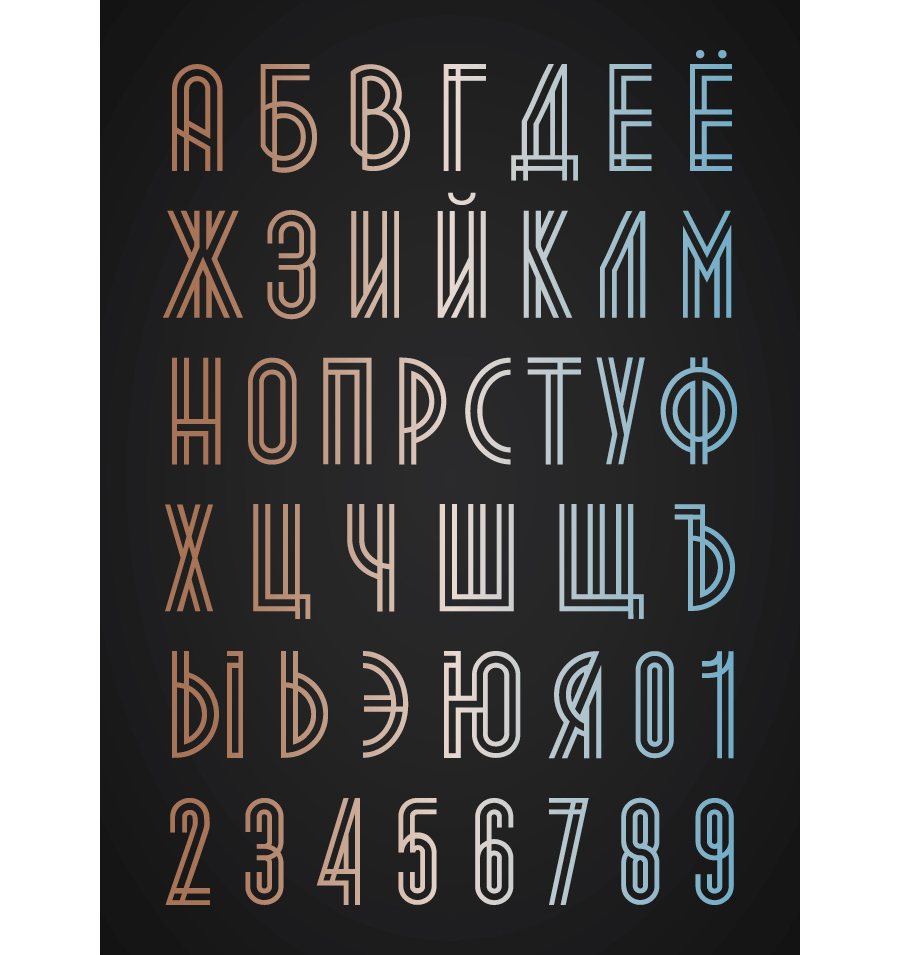
Коллекция современных часто минималистичных шрифтов с тонким рисунком букв.
Если у вас есть папка с ресурсами, наверняка в ней есть папка для шрифтов.
Однако со временем они могут устареть. Как насчет некоторых современных шрифтов для текущих логотипов?
Если вам нужно обновить имеющиеся у вас шрифты и добавить более современные и актуальные, взгляните на те, которые мы нашли. Наверняка некоторые из них можно использовать для своих проектов.
Ломбок
Мы начнем со шрифта, который довольно сильно противоречит тому, как формируются некоторые буквы. Он создан Александром Пьетром и состоит из разделенных форм, двойных линий и геометрических фигур.
Мы продолжаем с другим шрифтом, который выглядит пухлым. Вступление идеально подходит для логотипов, если они состоят из коротких слов (если они очень длинные, они могут выглядеть слишком нагроможденными).
Кроме того, если вы посмотрите на почерк, он не совсем «прямой». И дело в том, что некоторые буквы имеют небольшую округлость, из-за которой они кажутся кривыми. Это хорошо, потому что это граничит с совершенством, но в текстах больше естественности.
Адам.CG Pro
Это шрифт, вдохновленный шрифтом Futura, созданным Шреником Ганатрой. Он идеально подходит для логотипов, но его также можно использовать на веб-страницах, поскольку Это очень чисто и легко читается..
Один день
Создано Наврас Монир, этот шрифт характеризуется стилизацией, и некоторые буквы будут казаться обрезанными. Тем не менее, это не мешает им быть идеально читаемыми.
Классная Мариса
Это еще один из современных шрифтов для логотипов, который будет отлично смотреться в некоторых ваших проектах. Буква окончательная, хотя в ней есть более толстые части. Но что больше всего выделяется, так это глифы, орнаменты и некоторые лигатуры, которые заставляют вас немного поиграть с буквами. чтобы найти в них идеальный баланс.
Linnet
Когда мы впервые увидели шрифт Linotte, мы подумали о логотипах, связанных с детским сектором, дошкольным образованием… И это потому, что это шрифт с закругленными буквами. Шрифт без засечек может отлично смотреться для логотипов.
Его создателем является Жоэль Карруше.
вода
Этот шрифт один из тех, которые больше всего контрастируют своими буквами. Вы увидите, если вы посмотрите на написание нескольких слов (лучше заглавными буквами, чтобы эффект был более наглядным), вы увидите, что в то время как одни буквы имеют очень выраженные прямые линии, другие играют округлостью.
Таким образом, собирая их вместе, он привлекает внимание именно по этой причине.
И мы уже говорим вам, что в нижнем регистре будет другой контраст (если вы объедините его в своем проекте, вы можете получить очень хорошие результаты).
фонарто
Еще один из современных шрифтов для логотипов, который вы могли бы рассмотреть, — это этот. Он сочетает в себе классический стиль, но также и с модернизмом.
Шрифт был создан Арваном Сутанто, и некоторые буквы выделяются. так как у них есть отделка, которая привлекает внимание (например, O и A, хотя e также имеет особый оттенок.
Радника
Этот шрифт, созданный Альфрено Марко Прадилом, подходит для всего, а не только для логотипов. Читается очень легко и просто. Именно поэтому многие ей доверяют. Как особенность, если вы посмотрите на строчную букву а, она имеет небольшой наклон (как если бы у нее был немножко животик).
Однако можно найти и современные шрифты с более выразительным характером. Такие шрифты могут подойти брендам с новаторским духом, например, связанным с электроникой, автомобилями или космической промышленностью.
Когда дело доходит до читаемости при печати, большинство современных шрифтов хорошо работают на бумаге или других носителях.